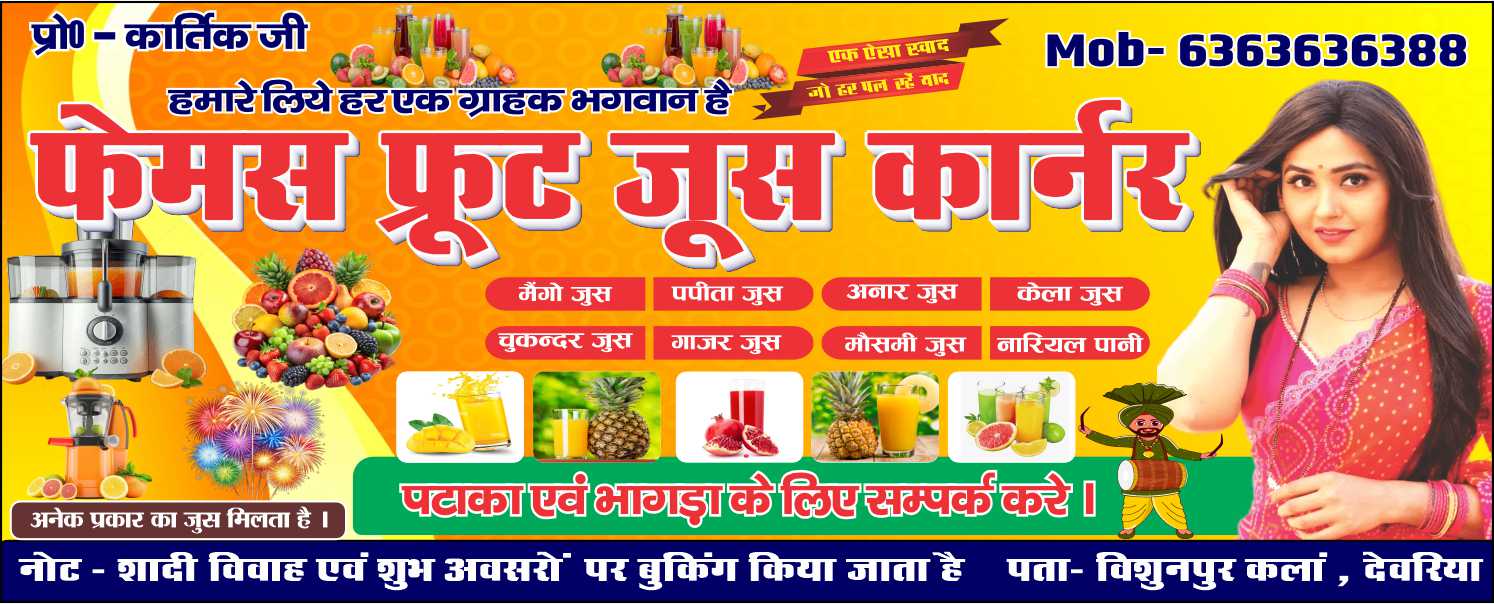
Fruit Juice Corner Banner CDR Design with Font
यह Famous Fruit Juice Corner (फेमस फ्रूट जूस कार्नर) का एक शानदार और रंगीन Flex Banner Design CDR File है। यदि आप जूस सेंटर, रिफ्रेशमेंट शॉप या कैटरिंग बिजनेस के लिए एक प्रोफेशनल विज्ञापन बोर्ड तैयार करना चाहते हैं, तो यह फाइल आपके लिए सर्वोत्तम है। इस डिजाइन में ताजे फलों के जूस जैसे मैंगो, पपीता, अनार, केला, चुकन्दर और मौसमी को बहुत ही आकर्षक तरीके से दर्शाया गया है।
डिजाइन की खासियत इसका वाइब्रेंट कलर पैलेट है, जिसमें पीले और नारंगी रंगों का उपयोग ताजगी और ऊर्जा का अहसास कराता है। “हमारे लिये हर एक ग्राहक भगवान है” जैसे प्रेरणादायक स्लोगन और “एक ऐसा स्वाद जो हर पल रहे याद” जैसी टैगलाइन ग्राहकों को जोड़ने का काम करती है। इसके अलावा, इसमें शादी-विवाह के शुभ अवसरों पर बुकिंग और ‘पटाखा एवं भांगड़ा’ के लिए संपर्क करने का अतिरिक्त विवरण भी दिया गया है, जो इसे मल्टीपर्पज बनाता है। यह फाइल पूरी तरह एडिटेबल है, जिससे आप प्रोप्राइटर का नाम, मोबाइल नंबर और पता (विशुनपुर कलां, देवरिया) आसानी से कस्टमाइज कर सकते हैं।
Product Highlights (मुख्य बिंदु)
• Fresh Look Design: ताजे फलों और जूस की हाई-क्वालिटी इमेजेस का उपयोग किया गया है।
• Dual Purpose Layout: जूस सेंटर के साथ-साथ इवेंट बुकिंग (भांगड़ा/पटाखा) की जानकारी के लिए भी जगह दी गई है।
• Highly Visible Text: मुख्य नाम ‘फेमस फ्रूट जूस कार्नर’ को बड़े और स्टाइलिश 3D इफेक्ट वाले फोंट्स में रखा गया है।